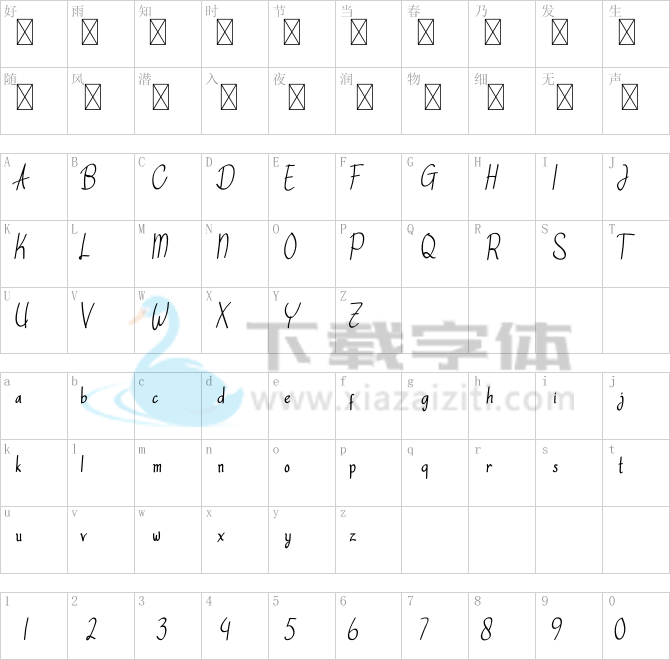
AshWord.otf字体下载
AshWord.otf字体下载,这款字体结构工整、笔画清晰,兼顾美观与易读性,适用于标题、正文、海报、包装、LOGO 等多种场景。字形优雅稳定,风格百搭耐看,适配日常排版与创意设计,让文字呈现更舒适、更具质感。AshWord.otf字体下载一笔一画,皆是细节,以均衡的比例、流畅的线条打造舒适视觉体验,字形端正大气,风格简约现代。无论是商业设计、品牌宣传还是日常排版,都能轻松驾驭,让文字更有格调与力量。AshWord.otf字体下载字体下载。